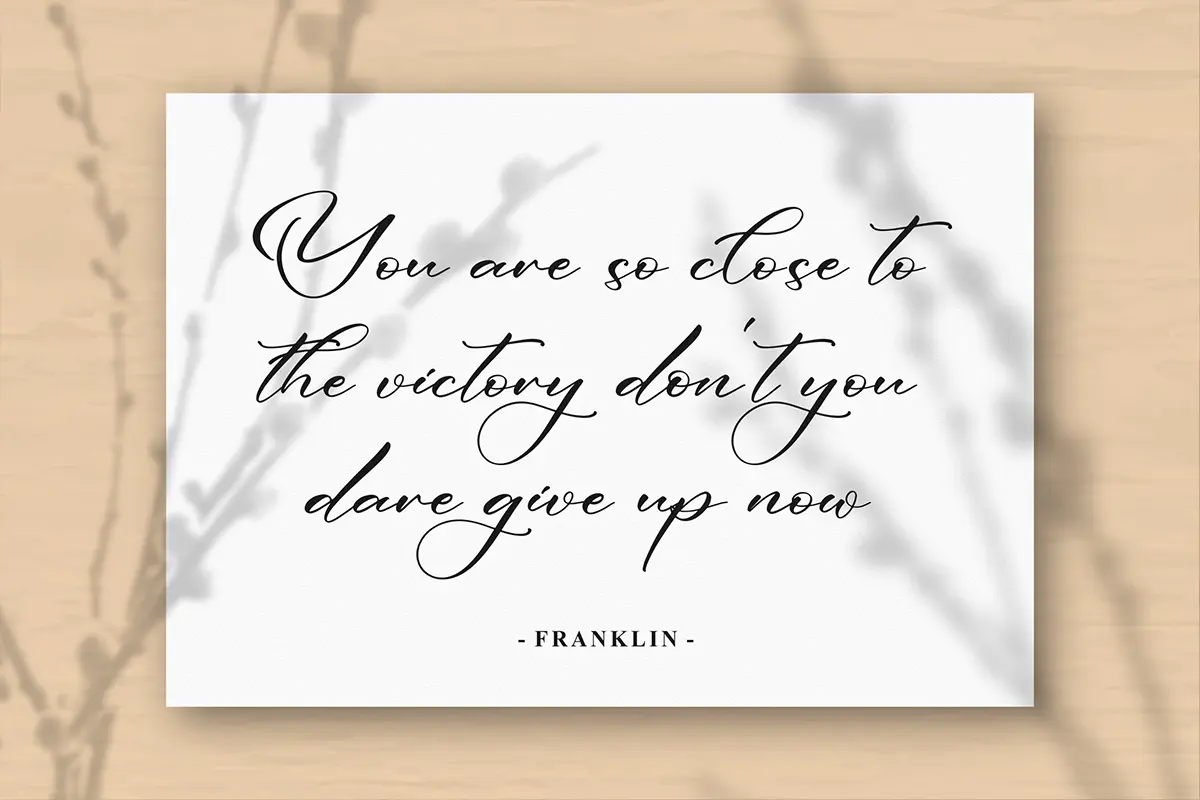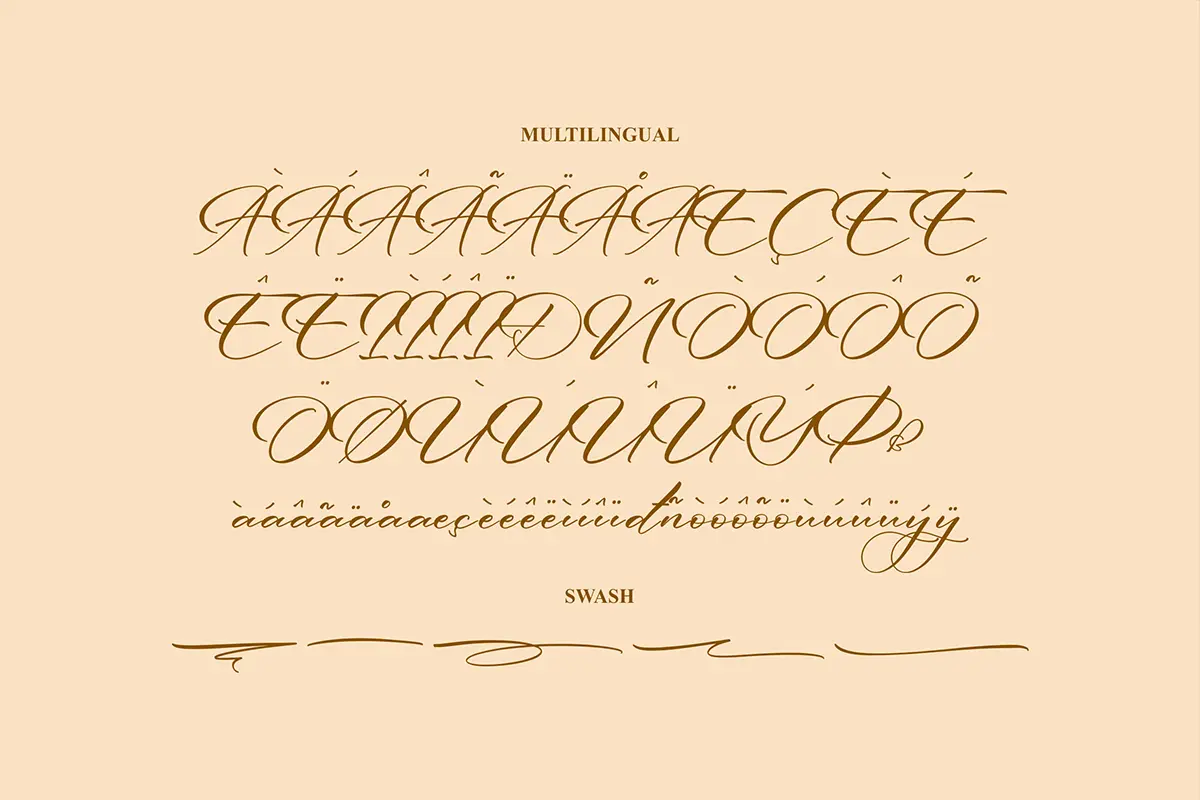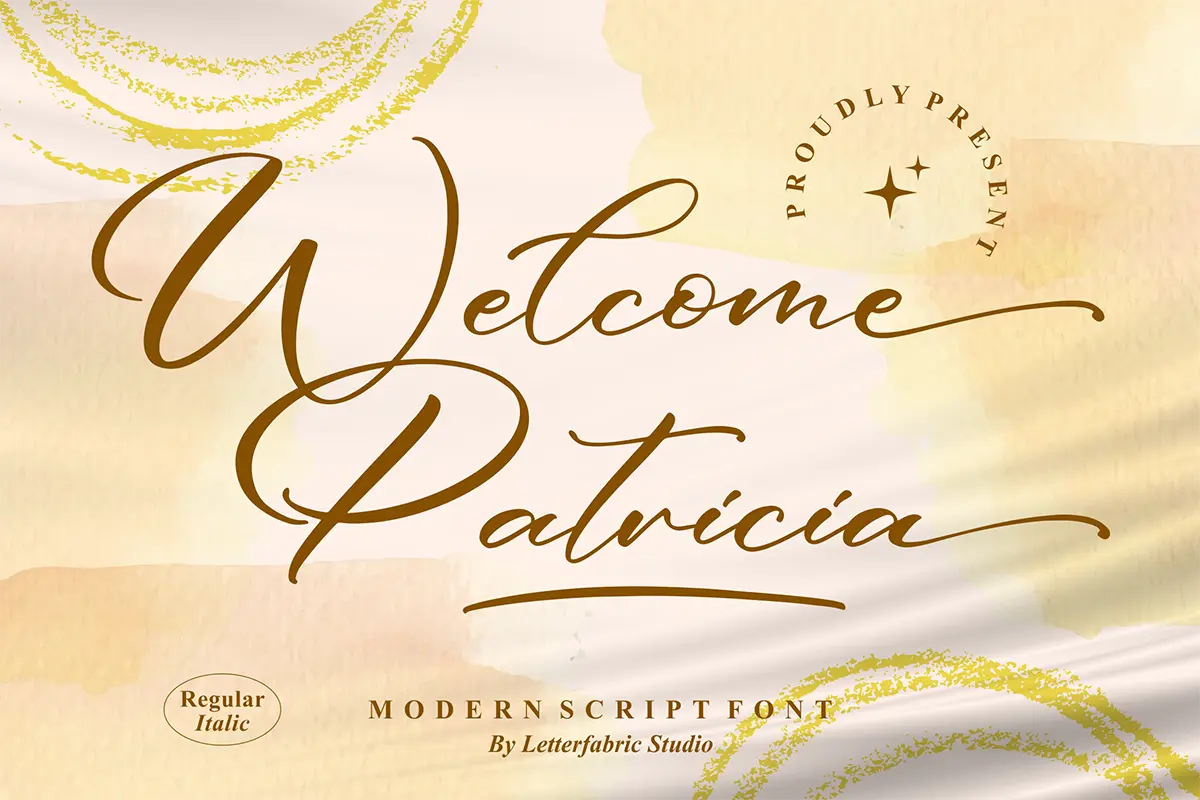
فونت اسکریپت مدرن و فانتزی
فونت Welcome Patricia یک فونت اسکریپت دوستداشتنی با کاراکترهای بازیگوش و جذاب است که بهنظر میرسد روی خط پایه میرقصند. این فونت ترکیبی از سبک مدرن و حالوهوای فانتزی دارد و به هر پروژهی طراحی جلوهای جادویی و خاص میبخشد.
⭐ ویژگیهای محصول:
- سبک: Script Font – فونت دستنویس مدرن و فانتزی
- طراحی: کاراکترهای روان، بازیگوش و جذاب
- PUA Encoded: دسترسی آسان به تمام گلیفها و سوئشها
🎯 موارد استفاده:
- طراحی کارت تبریک و دعوتنامههای فانتزی
- لوگوهای خلاقانه و برندهای هنری
- پوسترها و بنرهای تبلیغاتی شاد و مدرن
- بستهبندی محصولات سرگرمی و هنری
- پروژههای دیجیتال مثل وبسایت و شبکههای اجتماعی